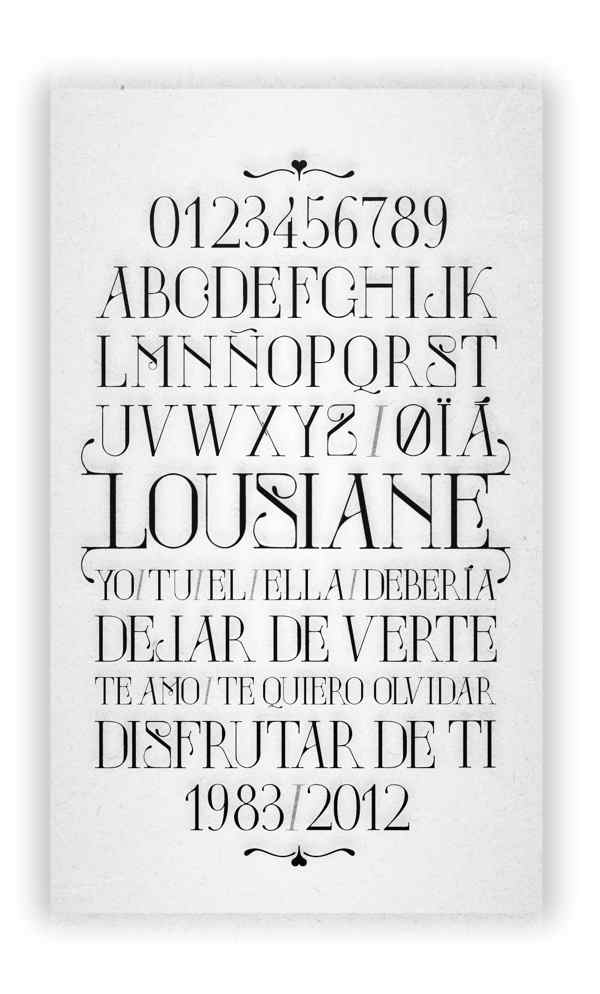
Aquí os dejo una tipografía gratuita diseñada por Juan José Rivas del Río. Es realmente preciosa y gratuita. Podéis descargarla pinchando en su nombre y visitando, ya de paso, toda su espectacular galería.